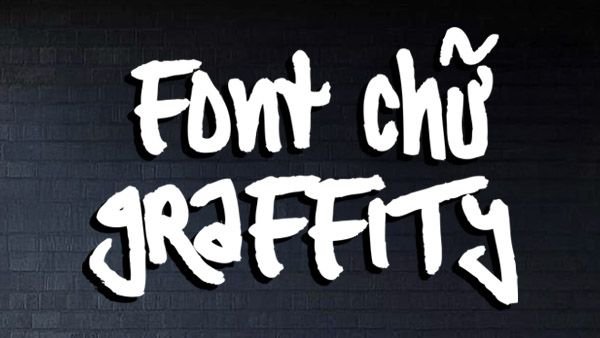
Graffiti là phong cách nghệ thuật đường phố đầy cá tính, mang trong mình hơi thở của sự tự do, phá cách và năng động. Việc sử dụng các bộ font Graffiti Việt hóa giúp người làm sáng tạo truyền tải những thông điệp mạnh mẽ, gây ấn tượng thị giác sâu sắc mà không gặp trở ngại về lỗi hiển thị tiếng Việt.
Đặc điểm ấn tượng của các bộ font Graffiti Việt hóa
Dòng font này mô phỏng các kỹ thuật vẽ tường bằng sơn xịt với những nét chữ dày, bo tròn dạng “bubble” hoặc những đường xước mang hiệu ứng chảy mực sinh động. Font chữ Graffiti Việt hóa được tinh chỉnh kỹ lưỡng hệ thống dấu tiếng Việt, giúp các ký tự có dấu không bị rời rạc hay làm hỏng cấu trúc đặc trưng của nghệ thuật đường phố. Sự đa dạng từ phong cách stencil, throw-up đến wildstyle giúp người dùng linh hoạt lựa chọn theo tinh thần của từng dự án.
Bên cạnh yếu tố thẩm mỹ, font chữ Graffiti Việt hóa còn sở hữu khả năng thu hút sự chú ý rất cao. Các bộ font như Sprite Graffiti font Việt hóa thường được yêu thích nhờ các nét vẽ chắc chắn, dễ đọc nhưng vẫn giữ được vẻ ngoài bụi bặm, phóng khoáng. Đây là phương án hiệu quả để tạo nên điểm nhấn khác biệt cho các ấn phẩm truyền thông, giúp bản thiết kế thoát khỏi những khuôn mẫu truyền thống và thể hiện rõ cá tính của thương hiệu.
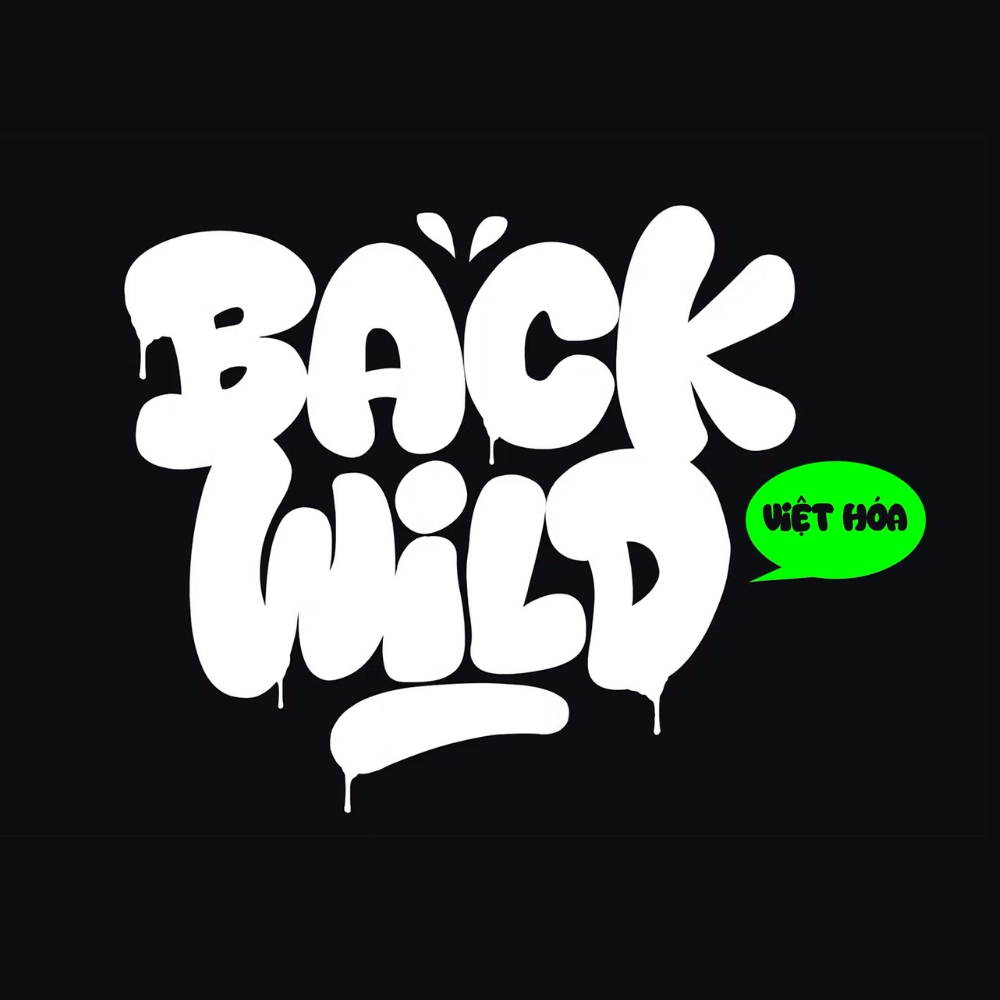
| Nhóm font tiêu biểu | Sprite Graffiti, Bubble, Stencil Việt hóa |
| Mục đích phù hợp | Tiêu đề, Poster, Bảng hiệu, Trang trí nội thất |
Tư vấn lựa chọn: Nếu dự án của bạn hướng đến sự vui tươi, gần gũi, hãy chọn các font dạng Bubble tròn trịa. Đối với các không gian cần sự mạnh mẽ, gai góc, các bộ font dạng Stencil hoặc nét vẽ chảy mực sẽ là gợi ý phù hợp để tạo hiệu ứng thị giác mạnh hơn.
03 Ứng dụng font chữ Graffiti Việt hóa vào thực tế
Nhờ vẻ ngoài giàu năng lượng và tính nghệ thuật cao, bộ font này mang lại giá trị thực tế khi được đưa vào các hạng mục trang trí và quảng bá các công trình mang phong cách hiện đại:
- Bảng hiệu cho Container Cafe & Pub: Những nét chữ Graffiti rất ăn ý khi xuất hiện trên bề mặt thép của nhà container. Đối với các mô hình kinh doanh trẻ trung, font chữ này giúp tạo nên một không gian mang đậm chất Urban, thu hút khách hàng yêu thích sự phá cách.
- Thiết kế Poster sự kiện thể thao và âm nhạc: Sử dụng Graffiti font free cho các tiêu đề chính giúp ấn phẩm truyền thông trở nên sống động, khơi gợi cảm hứng về sự vận động và năng động cho người xem.
- Trang trí nội thất Homestay phong cách đường phố: Bạn có thể dùng font này để vẽ tranh tường hoặc cắt chữ nổi làm điểm nhấn tại phòng khách, khu vực sinh hoạt chung của các khu nhà lắp ghép, tạo nên một không gian sống đầy nghệ thuật và khác biệt.
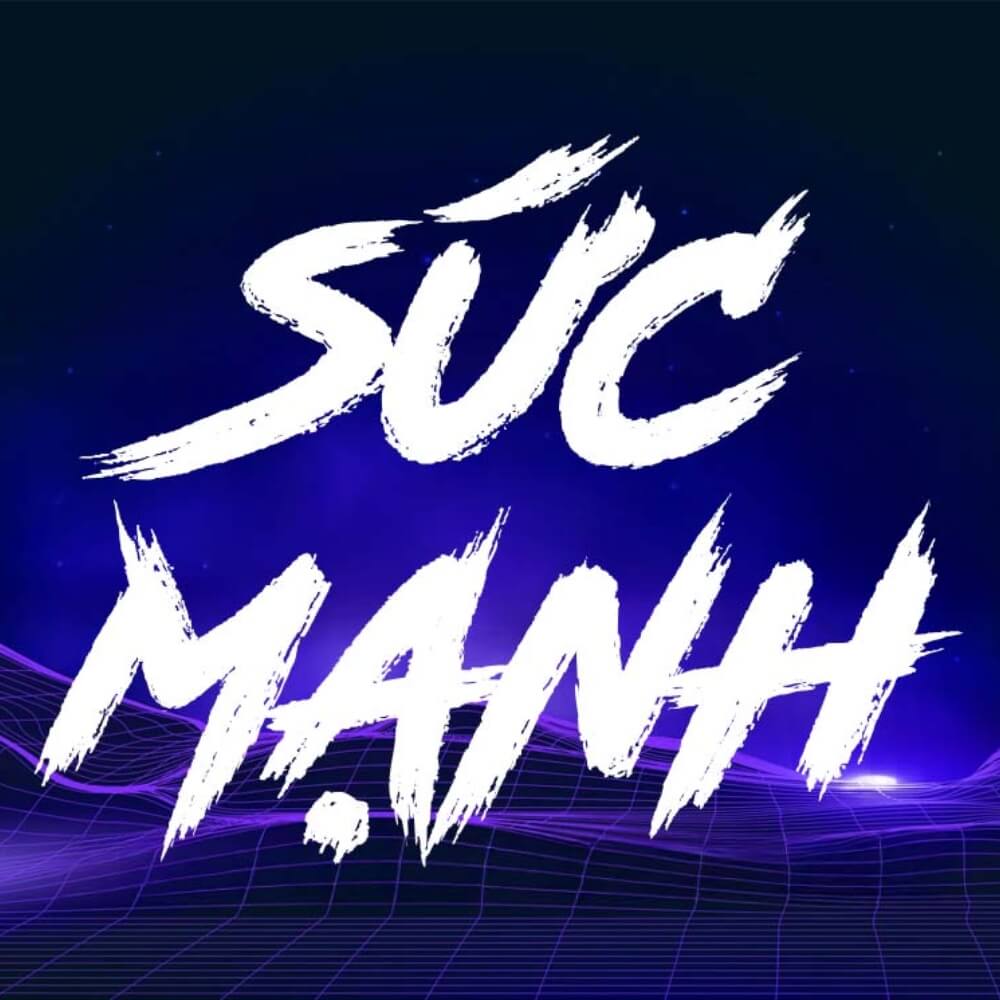
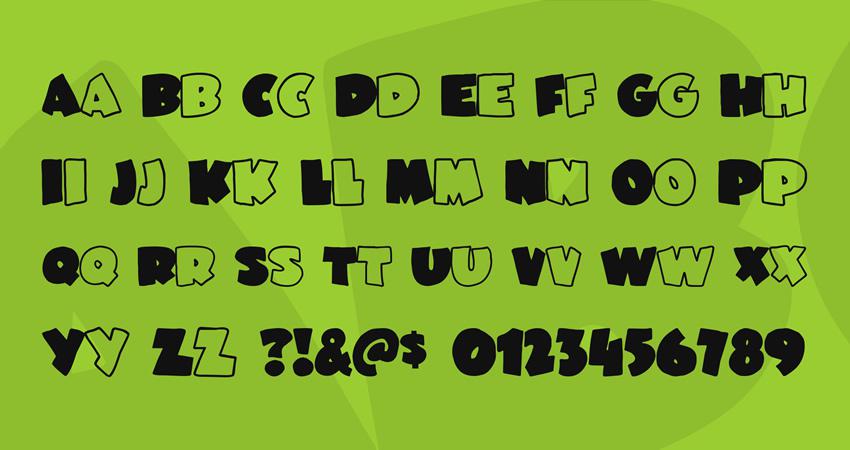
03 Lưu ý khi sử dụng font chữ Graffiti Việt hóa trong thiết kế
Để khai thác hiệu quả vẻ đẹp của dòng font đặc thù này mà không làm rối mắt người xem, người thiết kế nên lưu tâm một số kinh nghiệm sau:
- Kiểm soát khả năng đọc hiểu (Legibility): Do cấu trúc chữ Graffiti thường phức tạp và có nhiều chi tiết chồng lấn, bạn chỉ nên sử dụng cho các tiêu đề ngắn hoặc slogan. Tránh dùng cho các đoạn văn bản dài vì sẽ gây mỏi mắt và khó tiếp nhận thông tin.
- Lựa chọn màu sắc tương phản mạnh: Phong cách Graffiti thường gắn liền với sự rực rỡ. Việc phối hợp các tông màu nóng cùng viền chữ (outline) đậm sẽ giúp chữ nổi bật hơn trên các nền tường hoặc nền poster nhiều chi tiết.
- Phối hợp cùng font tối giản: Hãy để font Graffiti đóng vai trò là điểm nhấn duy nhất. Các phần thông tin phụ nên sử dụng font không chân (Sans-serif) đơn giản để cân bằng lại bố cục, giúp bản thiết kế trông chuyên nghiệp hơn.